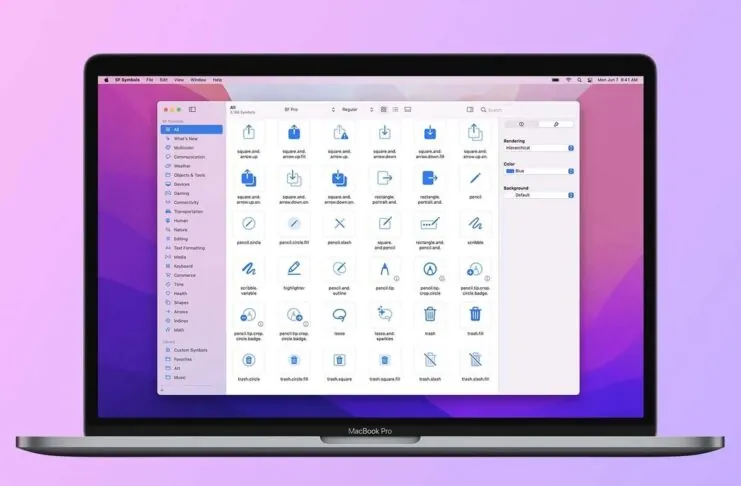
Oltre agli aggiornamenti per i vari sistemi operativi, in occasione dell’ultima conferenza mondiale degli sviluppatori (WWDC 2021) di giugno Apple ha rilasciato SF Symbols 3 beta, font che include oltre 600 nuove icone, ora disponibile aggiornato non solo per gli sviluppatori ma per tutti.
Questo font – segnala il sito 9to5mac – consiste in una libreria con oltre 3.100 simboli vari che gli sviluppatori possono usare nei loro progetti. Oltre a 600 nuove icone, SF Symbols 3 vanta peculiarità quali la possibilità di personalizzare i colori, un nuovo inspector e migliorie per la personalizzazione dei simboli.
“Con oltre 3100 simboli, SF Symbols è una libreria iconografica progettata per integrarsi perfettamente con San Francisco, il font di sistema per le piattaforme Apple. Symbols integra nove larghezze e tre scale, e si allinea automaticamente con le etichette di testo”, riferisce Apple, spiegando ancora che è possibile sfruttarlo in abbinamento a strumenti di editing vettoriale per creare simboli personalizzati che tengono conto di funzionalità di accessibilità.
Oltre a SF Symbols 3, Apple ha anche rilasciato le versioni aggiornate dei font San Francisco e New York, utilizzati in varie interfacce dei sistemi operativi di tutte le piattaforme Apple. Sia SF Symbols 3, sia gli altri font di Apple si possono scaricare dal sito della multinazionale di Cupertino riservato agli sviluppatori. Per installare SF Symbols 3 è richiesto macOS Catalina o seguenti.